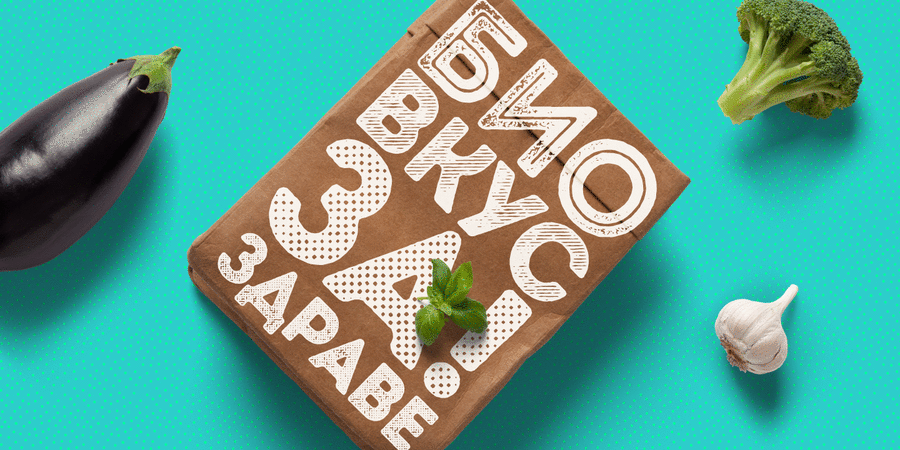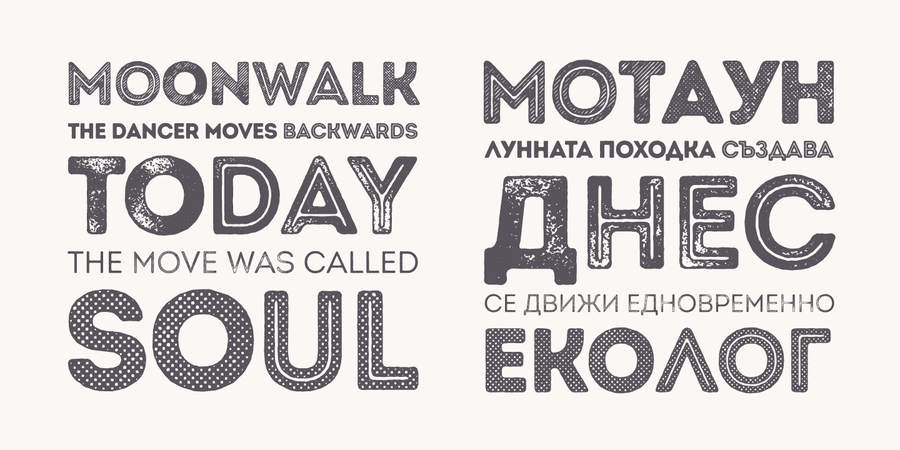
Contrast font pair with Skema Pro Livro Light (1 of 6)About Intro Rust G Base2Бесплатное начертание одной из крупнейших шрифтовых систем в мире Интро Раст, включающей 214 начертаний. Это огрубленная текстурная версия известного шрифта Интро. Система Интро Раст включает 4 семейства: Intro Rust, Intro Script, Intro Head и Intro Goodies. Она может применяться для создания почти всех видов дизайнерской продукции от полиграфии до веб-дизайна. Просто используйте воображение и ваши проекты станут более живыми, благодаря шрифтам системы Интро Раст. Хотите сделать поздравительную открытку или дизайн упаковки или даже айдентику? Смело экспериментируйте с паттернами и рисунками, рукописными версиями или теми классными начертаниями с точками и получайте современный успешный дизайнерский проект. Шрифт разработан Светославом Симовым, Ани Петровой и Радомиром Тинковым в 2015 году и выпущен фирмой Фонтфабрик. http://www.fontfabric.com/intro-rust/
Features of font family Intro Rust G Base2The hit of the decade:
Associations for font family Intro Rust G Base2Typeface personality and character:
hipster, Vintage, domestic, rude, notable, splashy, static, convincing, solid, reliable, conservative, honest, decrepit, senior, good quality, robust, iron, wooden, available, eco-friendly, spectacular, green, natural, warm, lamp, motivating, original, expressive, fashionable, high-quality, urban, severe, craft brewed, autumn, hot, fiery, incendiary
retail, grocery, stock, box, blacksmith, meat, carpenter, wood, handmade, cafe, snack, food, recreation, shop, farmer, pizza, entertainment, attraction, city, biscuit, steel-maker, dinner, burger, fall, equipment, tool, car, railway, steam locomotive, Instagram Typeface associated with age: